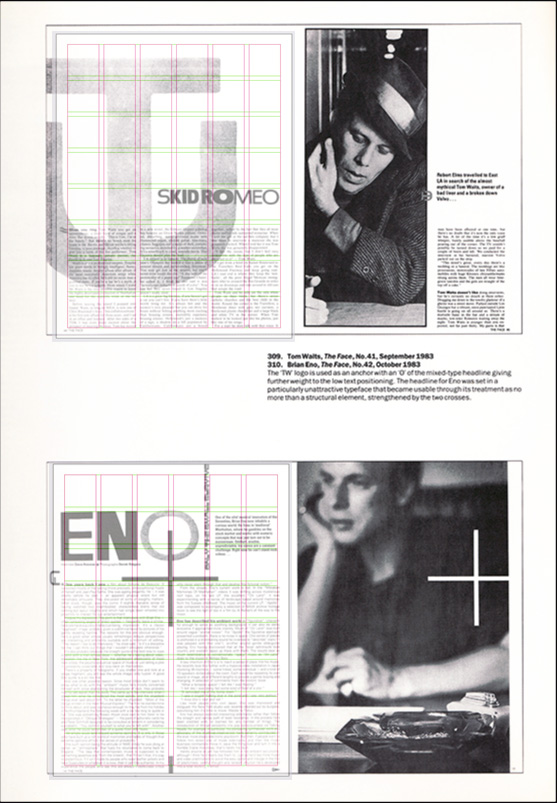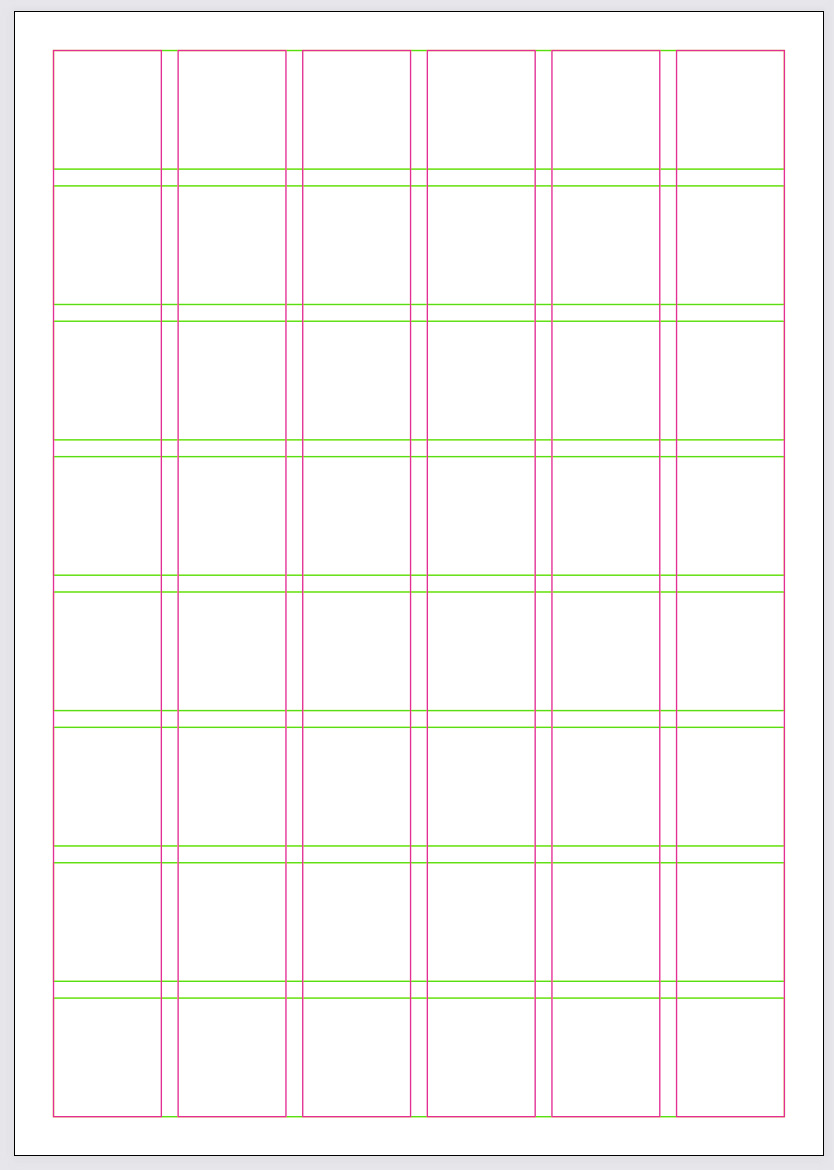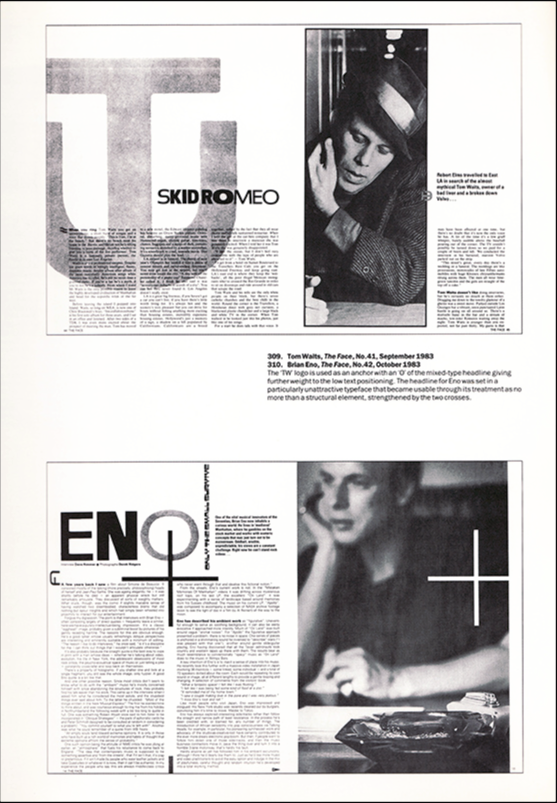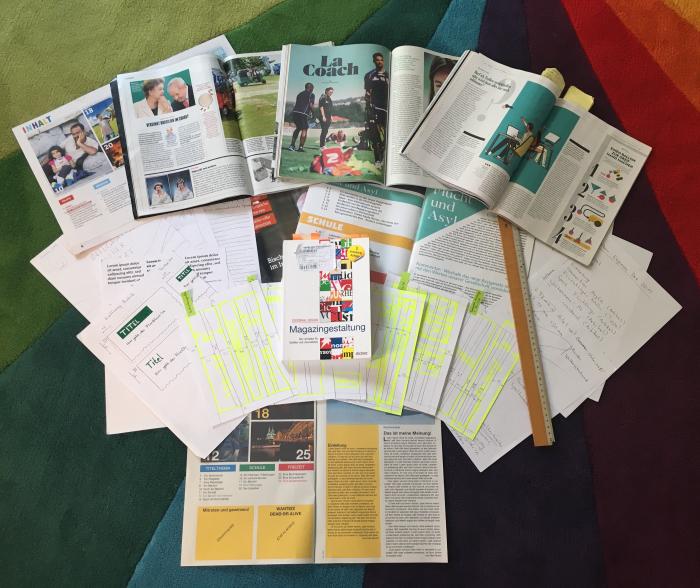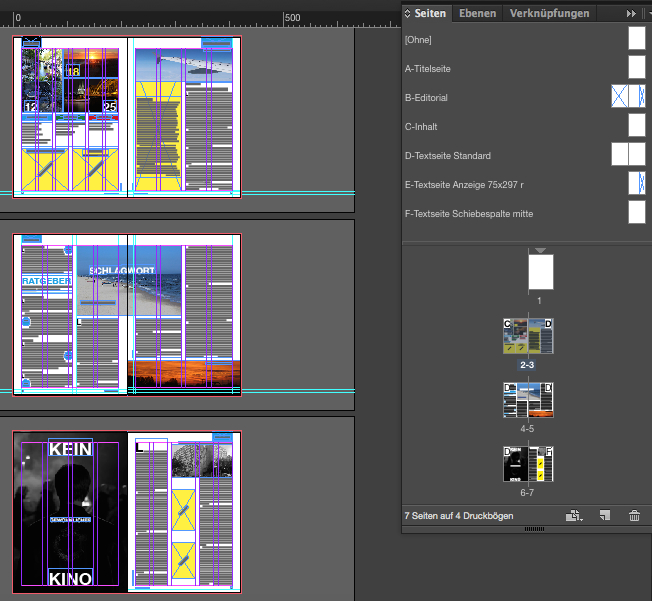
Typografie einer Schülerzeitung
Hier nochmal was von Brody ... mit ordentlich viel Text, wirkt aber gar nicht so.
Auch ein solches Layout könnte bei meiner vorgeschlagenen Vorgehensweise als Resultat herauskommen.  :nicken:
… Das soll doch nicht aussehen wie die vorbildlich gerasterte Apothekenrundschau mit Jugendlichkeit durch Schriftwechsel. …
Die Hinweise von Kathrinvdm finde ich schon viel zu viel. Das soll doch nicht aussehen wie die vorbildlich gerasterte Apothekenrundschau mit Jugendlichkeit durch Schriftwechsel.
Hier wäre mal ein einfaches Gestaltungsraster, das viele Möglichkeiten offenhält: 6 halbe Spalten – und horizontal dann nochmal in acht Segmente unterteilt, wenn man das will/braucht ... Das sollte für den Anfang reichen.
Garamond und Futura ist super - wenn man's noch altbackener möchte.
Garamond und Futura wirken in etwa so was wie zeitlos. Es ist eine relativ bewährte Kombination, ähnlich wie Palationo oder Bodoni als Brotschrift und dazu die Futura. Letztere Kombinationen wirken dann eher etwas moderner? Bei den gezeigten Beispielseiten wird die Schrift nur sehr wenig zum Eindruck der Modernität beitragen. Da sind Grafiken, Anordnung aller Elemente und Satzspiegel sehr viel bedeutender. Eine bewährte Schrift(-kombination) die nur wenig Probleme macht ist da IMHO von Vorteil. Ein anderer Poster wies auch schon auf diesen Sachverhalt hin.
Mein Ansatz war einfach nur die Verwendung von pflegeleichten Schrift(kombination)en des geringsten Misstrauens. Und bei einem in deutscher Sprache gesetzten Magazin sind IMHO französische Renaissance-Antiqua erste Wahl, vor Barockantiqua, wie die Times. Ich habe die Garamond nur als Beispiel genannt, es muss nicht immer Garamond sein. Du hast ja die Links auf die Listen gesetzt, aus denen der Frager sich die freien Schriften auswählen kann. Er hätte mit einer solchen Brotschrift (Schrift für den Fließtext, welche dem Drucker das Brot auf dem Tisch bringt) die wenigsten Probleme zu erwarten und könnte aus einem reichen Fundus an Beispielen Inspirationen holen.
Dieser Ansatz wäre IMHO inkompatibel zu den Vorschlägen sich an N. Brody zu orientieren. Ein Design dieser Art sauber und lesbar zu gestalten erfordert sehr viel Zeit und Übung. Da sollte der Frager erst mal „reinwachsen“. Als hauptberuflicher Schüler hat er garantiert keine Zeit viele Stunden am Rechner zu üben. Er könnte diesen Stil dann aber an einzelnen Seiten, so wie die von mir bereits kritisierte Seite mit dem einen Bild, ausprobieren und üben. Jaja, ist auch nicht gerade ein Beispiel der reinen Lehre, aber eine gute Übung.
Zur Schriftenkombi möchte ich noch das Sans/Slab-Paar Graublau anbringen, die ich sehr spannend finde.
Ist Eure Zeitung eher magazinartig? Also wird auch auf hochwertigem Papier gedruckt und gebunden? Oder werden DIN A4-Seiten kopiert und zusammengetackert? Auch das beeinflusst meiner Meinung nach die Schriftwahl. Im letzteren Falle ist die zeitlose Garamond einer S-Klasse gleich mit einem Trabbi-Motor* ;)
zuerst mal muss ich Martins Ausführungen weitgehend zustimmen, habe da aber noch die eine oder andere Anmerkung.
GGL sagt: Eine Schrift ohne Anwendung ist wie eine Blume ohne Duft. Garamond und Futura können nicht per se altbacken sein. Es sind klassische Werkzeuge, und wenn sie altbacken aussehen, sind sie altbacken angeordnet worden, und dann würde an derselben Stelle jede andere ähnliche Type aus unserer Zeit genauso altbacken aussehen. In dieser Diskussion wird die Schrift aberwitzig überbewertet, weil die Kenntnisse zur Anwendung sicherlich gänzlich fehlen. Der Normalfall ist doch, daß der Laie eine Walbaum von einer Garamond erst unterscheiden kann, nachdem er drei Minuten draufgestarrt und man ihm ein paar Hinweise gegeben hat. Geschweige daß er Excelsior und Garamond auseinanderhalten könnte.
Alles drei sind IMHO sehr gut lesbare Schriften und ich mag auch alle drei Genannten. Allerdings wird bei der Walbaum bei dem einen oder anderen Leser dann doch die Assoziation mit der Financial Times auftauchen? Ich würde das zwar als vernachlässigbar sehen, aber im falschen Kontext kann das nach hinten los gehen.
Um Anwendung von Schrift, um Typografie zu provozieren, wäre es interessant, überhaupt einmal nur eine einzige Schrift für alles zu verwenden, in gewöhnlich und kursiv. Den Rest an Unterscheidung mit Größe, Farbe und Anordnung produzieren. Die meisten Anfänger glauben, daß die Auswahl der Schrift die halbe oder ganze Miete wäre, dabei sind es nur fünf Prozent. Das Entwerfen mit zwei Schriftschnitten, Größen und Anordnungen, auch Ornamenten und Flächen, macht übrigens auch mehr Spaß als darüber nachzudenken, welche Formprinzipien einzelne Schriften zeigen und wie sie zusammenpassen könnten. Man kann bei einer einzelnen Schrift auch gegen keine Regel der Schriftmischung verstoßen. Typografie ist keine Formelsammlung.
Bei mir gehört aber zur Typografie auch so was wie eine kleine Formelsammlung. Ok, das sind Abschätzungen unter welchen Randbedingungen welche Schriften mehr Probleme machen als andere. Und so richtige Berechnungen sind das auch nicht ... Eigentlich sind das eher Erfahungswerte zu einigen Parametern zugeordnet ...